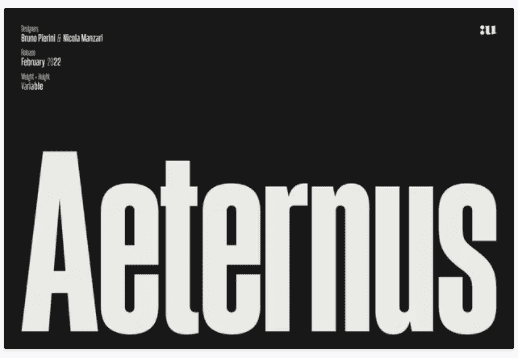
"Aeternus" - новый геометрический шрифт Sans Serif Variable с соответствующим курсивом. Сочетание различных высот и весов обеспечивает универсальность при любом использовании текста и открывает целый мир новых возможностей.
Начиная с двух постоянных высот, Nano и Tall, это семейство шрифтов использует вариации веса и предлагает полный набор из девяти вариантов, включая все веса от тонкого до тяжелого. Отличительной особенностью этого переменного шрифта является возможность варьировать высоту, просто сохраняя постоянными веса тонкого и тяжелого.
Оптимизирован для оформления заголовков, современного брендинга, веб-дизайна, UI/UX-дизайна, одежды, больших печатных форматов.